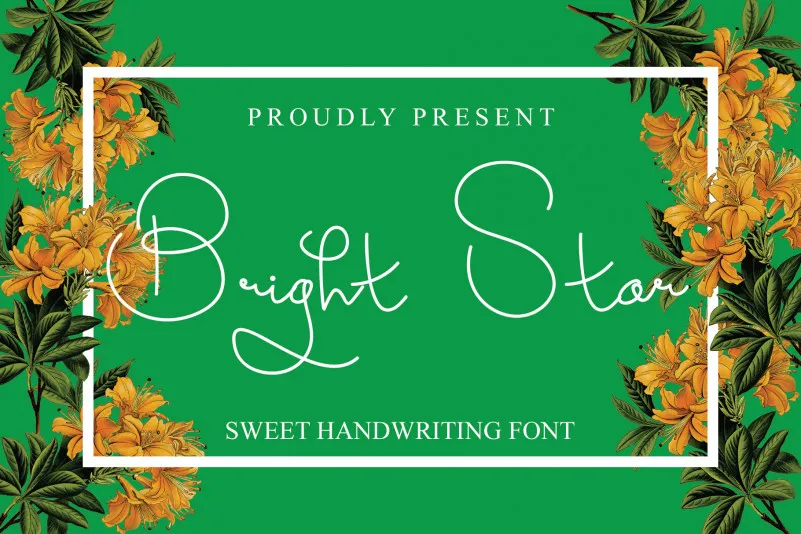
Bright Star Font – Download Grátis
Aqui está uma descrição curta e envolvente para a página de download da font ‘Bright Star’, adequada à categoria de fuentes escritas à mão: ‘Veçamos um pouco do encanto e do tempo que passam em nossa era digital com “Bright Star Font”, uma linda fonte escrita à mão. Ideal para criar logomarcas, branding e frases impactantes, esta font oferece uma sensação única e encantadora a cada letra. Seja você um criador de gráficos ou designer de logos, este é o tipo perfeito para tornar seu trabalho inovador e vívido.’